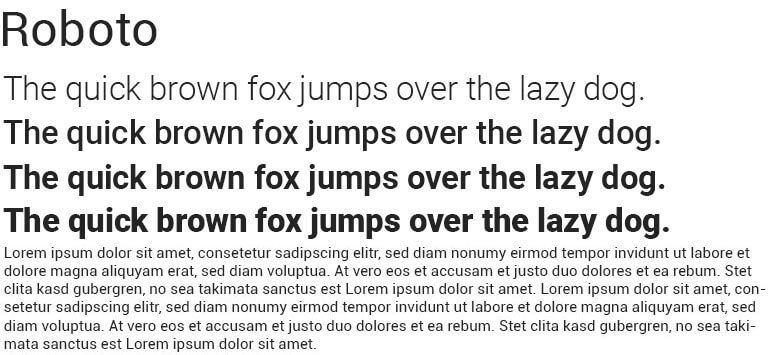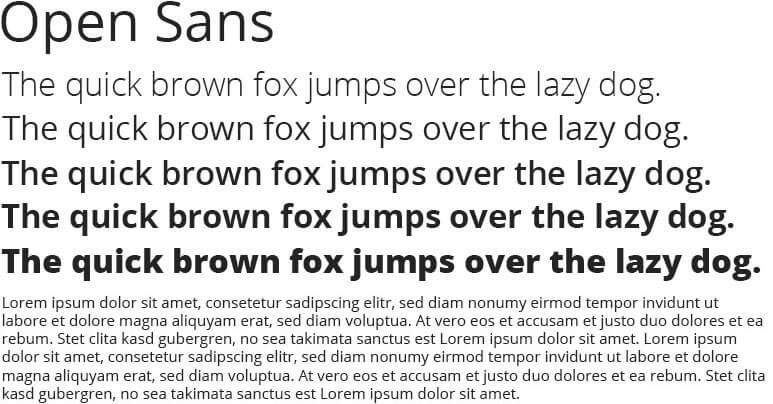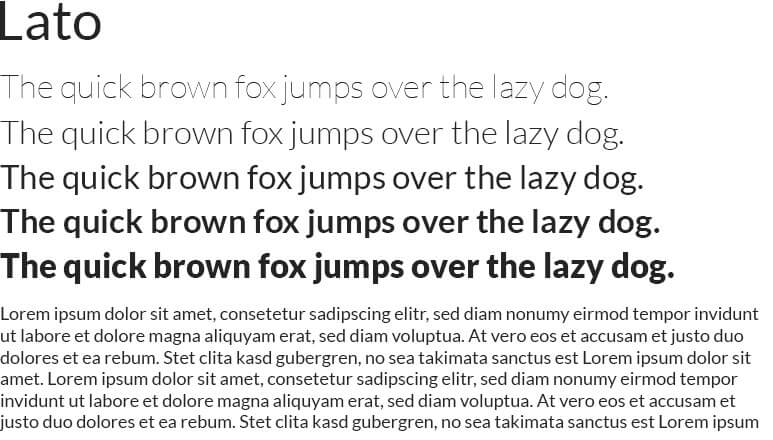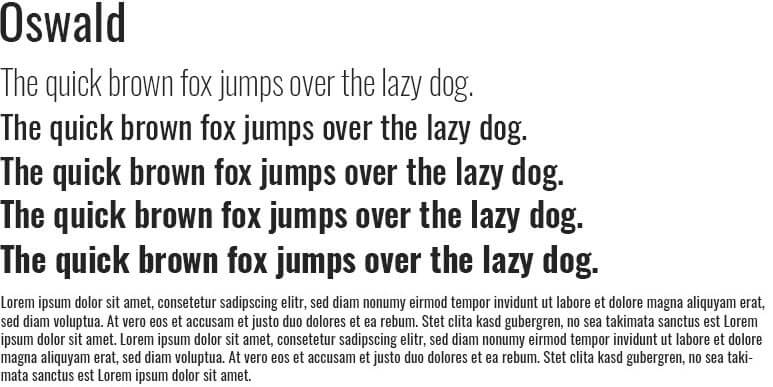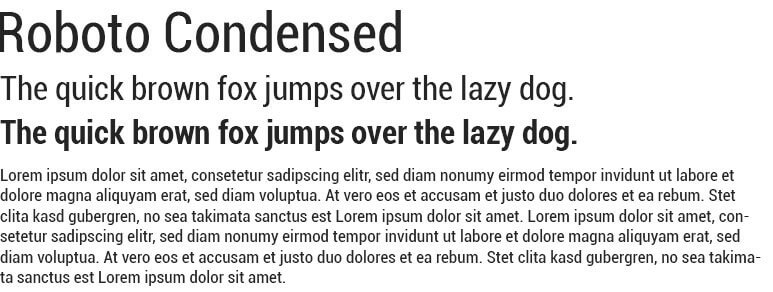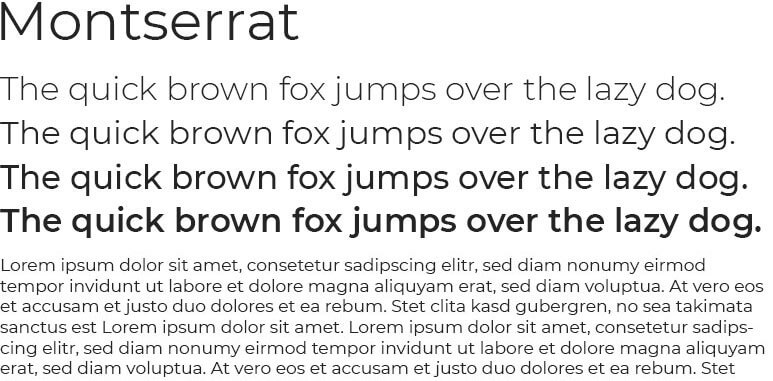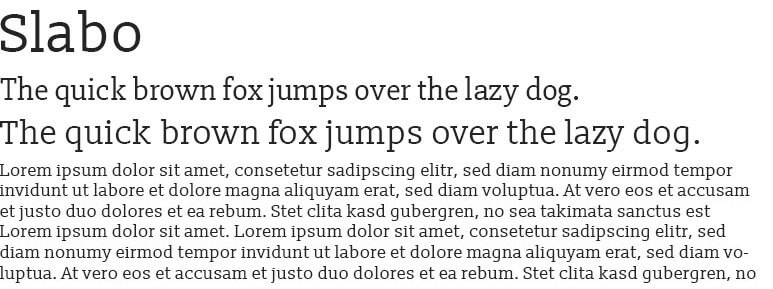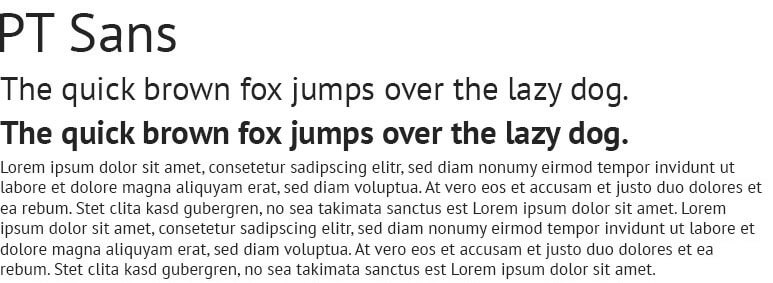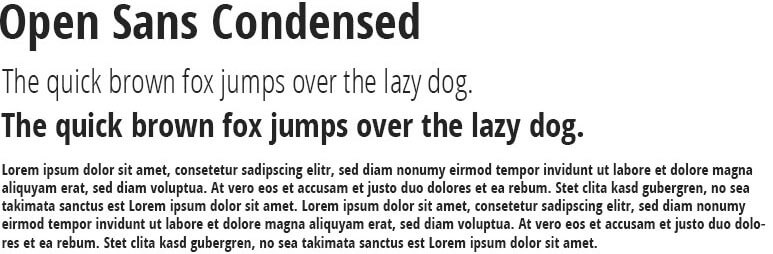
Google stellt mit Google Fonts eine riesige Schriften-Plattform für Webdesigner bereit. Hier findest du über 1.900 Schriften zur Einbindung in deine Website. Leider kann die große Auswahl an Schriften auch sehr verwirren. In diesem Artikel möchte ich dir die beliebtesten Google Webfonts zeigen. Zudem gibt es auch noch ein paar Geheim- Webfonts Tipps von mir.
Die beste Google Webfont hängt auch davon ab, was für ein Webprojekt du realisieren willst. Eine Schrift hat immer auch einen Charakter und unterstreicht damit auch die Coporate Identity bzw. das subjektive Gefühl. Zudem kannst du auch die Lesbarkeit und die Konversionsrate deiner Website durch die passendere Schrift verbessern.
Mit über 38 Billionen Font Views sind die Google Webfonts der Anlaufpunkt für alle Webdesigner auf der Suche nach der besten Schrift für Ihr Webprojekt. Aber Achtung: Mit der DSGVO ist das Einbinden von Google Webfonts auch eine rechtliche Frage. Im Zweifel solltest du die Google Web Fonts einfach lokal einbinden.
Aber nun genug geschrieben. Hier sind nun die besten Google Webfonts:
Das Wichtigste in Kürze:
- Zwei Schriften reichen für die meisten Websites – eine für Überschriften, eine für Fließtext
- Auf Schriftschnitte achten: Eine Familie mit mehreren Stärken ist flexibler als drei einzelne Schriften
- Ladezeit beachten: Jeder zusätzliche Schnitt kostet Performance
Die beliebtesten Google Webfonts
Um eine objektive Liste mit den besten Google Fonts zu erstellen, habe ich Google Font Analytics genutzt. Das sind die meist verwendetsten Google Web Fonts:
Roboto
Roboto wurde 2011 von Christian Robertson entwickelt. Google wollte eine Schrift für Android Geräte und Roboto war geboren. Die Kurven verleihen der geometrischen Grundformen der Font eine gewisse Dynamik. Diese sucht man unter anderen bei Grotesk Fonts vergeblich und macht die Robot damit einzigartig. Sehr schöne und lesbare Schrift, die sich nicht nur für technische Themen eignet.
Open Sans
Auch die Open Sans wurde 2011 im Auftrag von Google für Android Devices von Steve Matteson designed. Die Open Sans basiert auf der Droid Sans, ist jedoch etwas weiter. Diese Google Font ist eine sehr beliebte Flat Design Schriftart. Die Open Sans hat eine sehr gute Lesbarkeit aber auch Charakter. Dabei eignet sich die Open Sans für fast jeden Einsatzbereich. Zudem ist die Schrift auch sehr gut mit anderen Schirftarten kombinierbar. Mein Tipp!
Lato
Die Lato wurde von Łukasz Dziedzic im Jahr 2010 für eine polnische Bank entworfen. Lato ist übrigens polnisch und bedeutet „Sommer“. Die Lato gibt es in neun Schriftschnitten und lässt so viele Möglichkeiten des Einsatzes. Ich benutze die Lato auch für meinen Blog als Light Variante. Dziedzic wollte eine transparent erscheinende Font im Fließtext, jedoch auch eine charakteristische Schrift, wenn es um große Letter geht. Die halbrunden Details geben der Lato eine warme Ausstrahlung, während die starke Struktur für Stärke und Seriösität sorgt. Deshalb eignet sich diese Google Webfont ebenfalls für viele Anwendungen – egal ob Web oder Print.
Oswald
Die Oswald Font wurde von Vernon Adams 2011 als Remake der klassischen „Alternate Gothic“ entwickelt. Die Anpassung wurden für das Web vorgenommen um eine bessere Anzeigequalität auf Pixel-Screens zu erzeugen. Die Oswald eignet sich gut für knackige Headlines. Mit 6 Schriftschnitten lässt sie dir auch genügend Spielraum für den Einsatz. Über die Jahre erhielt die Oswald immer wieder Updates und Überarbeitungen.
Roboto Condensed
Die Roboto Condensed ist eine Alternative zur Roboto. Du kannst die Roboto Condensed überall da verwenden, wo wenig Platz ist. Allerdings wird durch den Condensed Schnitt auch die Lesbarkeit beeinflusst. Trotzdem ist die Roboto Condensed eine der beliebtesten Schriften.
Montserrat
Die Montserrat ist eine Webschrift, die von Julieta Ulanovsky entwickelt wurde. Ihren Namen hat diese Google Font von einem historischen Viertel in Buenos Aires. Julieta lies sich von den Beschilderungen in diesem Viertel inspirieren und sammelte 5000 Dollar bei Kickstarter für die Entwicklung der Montserrat. Wie versprochen, stellt sie die Lizenz für die Montserrat auch Google zur Verfügung. Mittlerweile ist die Montserrat ebenfalls eine sehr beliebte Google Web Font.
Slabo 27px
Der Designer John Hudson entwickelte die Slabo für Online Werbung und andere netzbezogene Anwendungen. Die Slabo 27px (der große Bruder der Slabo 13px) steht leider nur in einem Schnitt (Regular 400) zur Verfügung. Dennoch ist dieser Font bei Google Web Fonts sehr beliebt. Dabei eignet sich die Slabo 27px eher als Headline. Die Schrift harmoniert mit der Roboto als Fließtextschrift oder auch mit der Source Sans Pro.
Source Sans Pro
Die Source Sans Pro wurde von Paul D. Hunt für Adobe als erste Open Source Font entwickelt. Diese Schrift hat ganz klar eine technische Anmutung. Deshalb wurde die Schrift auch für Benutzeroberflächen konzipiert. Die Schrift ließ sich in seiner Klarheit und Lesbarkeit von den amerikanischen Gotik Schriften des 20. Jahrhundert inspirieren. Glyphenformen wurden vereinfacht und kleine Details wiederum hinzugefügt um eine bessere Unterscheidbarkeit der einzelnen Glyphen zu erreichen. Die Source Sans Pro kommt breiter als vergleichbare gotische Schriften.